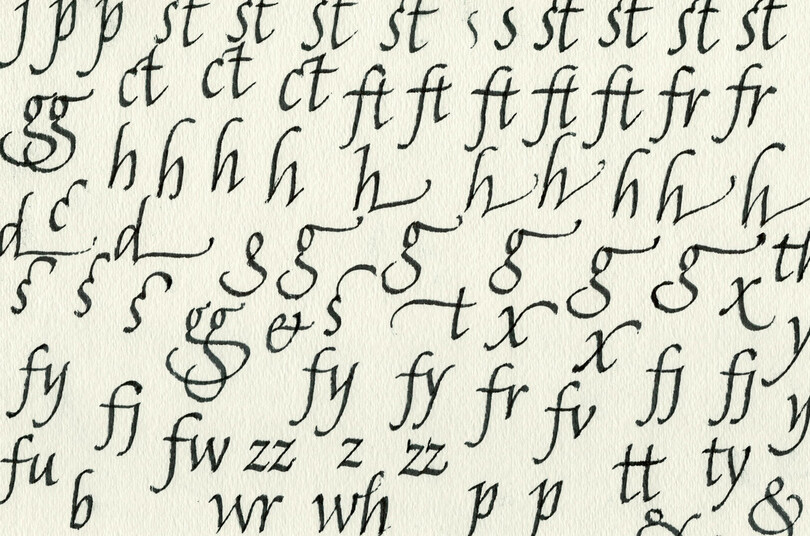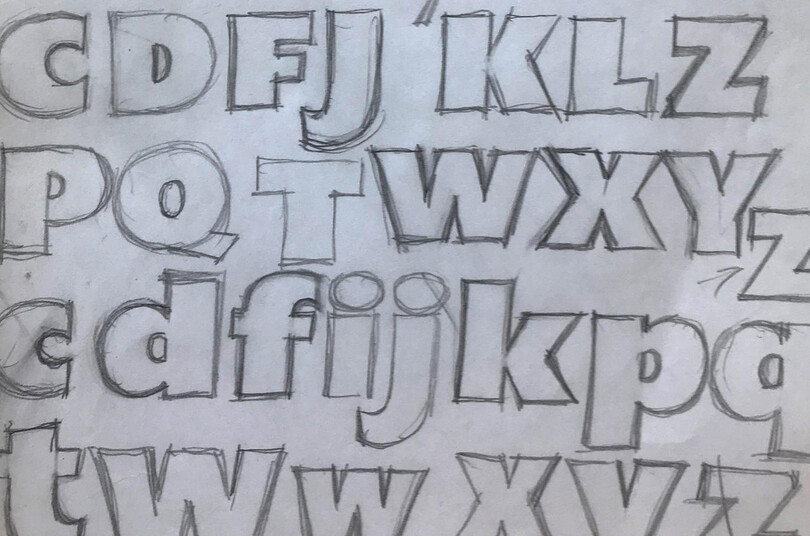
Hinter den Zeichen: Carl Crossgrove, Monotype Studio.
„ Bei der Entwicklung von Exklusivschriften für Unternehmen beginnen wir meist mit dem Markenkern und dem Bild, das die Konsumenten von der Marke haben. Außerdem klären wir, in welchen Umgebungen und Märkten die neue Schrift in Zukunft eingesetzt werden soll. “
Carl Crossgrove
„Hinter den Zeichen“ ist eine Serie von Designer-Interviews, in der die Schöpferinnen und Schöpfer der Fonts vorgestellt werden, die wir lieben und gerne benutzen.
In dieser Folge stellen wir Carl Crossgrove vor, Senior Type Designer beim Monotype-Studio. Von Carls frühem Interesse an Kalligrafie und Zeichnen, bis zu seiner Schul- und Hochschulzeit, als er bildende Kunst und Buchgestaltung studierte, faszinierten ihn dauerhaft die Form von Buchstaben. Neben der Erstellung neuer Schriften für die Monotype Library entwirft Carl auch Exklusivschriften, wobei er an zahlreichen Corporate-Branding-Initiativen mitgewirkt hat.
Erfolgreich starten
Die meisten neuen Schriften entstehen, weil es eine Lücke in der breiten Palette des Font-Angebots zu füllen gilt. Die Ursachen hierfür sind vielfältig: Manche Schriften werden eigens für bestimmte Aufgaben, neue Medien oder Umgebungen entwickelt; andere, um ein bestimmtes Gefühl oder eine Stimmung auszudrücken. Sehr häufig werden auch vergessene Entwürfe wiederentdeckt und für die Herausforderungen des digitalen Zeitalters aktualisiert und erweitert.
Am Beginn eines jeden Projekts steht der ständige Austausch mit Designern und Schriftnutzern, um genau zu verstehen, was sie benötigen und wie sich dies auf die Entwicklung der Schrift niederschlägt. Im Monotype Studio gibt es über 50 Menschen, die täglich Buchstabenformen „ein und ausatmen“. Carl ist einer von ihnen.
Wie viele Schriftentwerfer beginnt er mit einer handgezeichneten Skizze, bevor der Prozess am Bildschirm fortgeführt wird. „Ich habe schon immer gerne gezeichnet, auch Buchstaben, also ist das Skizzieren und Korrigieren der Beginn jeder neuen Schrift. Manchmal zieht sich dieser Prozess, mit nur wenigen Buchstaben, über eine lange Zeitspanne hin. Manchmal ist die Grundidee schnell entwickelt, und ich lege in einer Sitzung die Basis für Groß- und Kleinschreibung, deren Kursivformen  sowie das Strichstärken-Modell.
Schriftskizze
„Manche Entwürfe sollen eine ganz spezielle Stimmung transportieren“, erläutert Crossgrove. „So habe ich beispielsweise Amarone entworfen, um eine Lücke im dichten Feld der Schreibschriften zu füllen – kalligraphisch und ausgefranst, aber doch gut lesbar. Die Blockschrift Cavolini wurde speziell für kleinere Bildschirme weiterentwickelt; ursprünglich war sie als Betriebssystem-Font für die Handschrift-Erkennung eines PDA-Notepads gedacht: So bietet sich stets ein Spektrum an Aufgaben und Varietäten für Schriften an.“
Er ergänzt: „In der Papier-und-Stift-Phase, wo es vor allem um die Konturen der Buchstaben geht, erreicht man nur einen gewissen Grad an Vollständigkeit: alles noch ziemlich provisorisch und chaotisch. Solange die Umrisse nicht gefüllt sind, bleibt weitgehend unklar, wie die Schrift irgendwann mal schwarz auf weiß wirken wird.“
Zusammen mit Charles Nix und Juan Villanueva war Crossgrove Teil des Monotype Studio-Teams, das Walbaum restaurierte, eine viel zu wenig beachtete, 200 Jahre alte und dennoch zeitgemäße Serif-Familie.  Obwohl solche Revivals auf vorhandenem Vorlagen basieren und nicht auf einem weißen Blatt entstehen, haben sie das gleiche Ziel wie komplett neue Designs: eine Lücke zu füllen beziehungsweise etwas Neues ins Spiel zu bringen..
Im Falle von Walbaum ging es darum, ein prächtiges Arbeitstier für das digitale Zeitalter zu modernisieren, so dass man ihre Wärme, ihren Charakter und ihre vielfältigen Verzierungen und Schnörkel neu genießen kann.
„Wir fanden es bedauerlich, dass die Schönheit und Nützlichkeit der Originale durch jahrzehntelange Formatkonvertierungen im Wesentlichen verloren gegangen sind und sich von den Originalen entfernt hatten“, ergänzt Crossgrove. „Unser Type Director Charles Nix  reiste rund um die Welt, um Originalmaterial zu beschaffen. Wir beide untersuchten und vermaßen gewissenhaft die Originale, um sicherzustellen, dass die digitale Neuinterpretation den Geist der Ursprungsentwürfe atmet.“
Für Marken entwickeln
Schriftgestalter werden häufig auch von großen Unternehmen gebeten, eine Lücken zu schließen. Exklusivschriftn sind ein wesentlicher Bestandteil des Portfolios vom Monotype Studio, darunter aktuelle Projekte für Santander, Alibaba, Tencent und Toyota.
Die meisten Marken erwarten, sich mit einer eigenen Schriften vom Wettbewerb abzuheben und ihren Bekanntheit zu festigen. Oder sie wollen die Lesbarkeit quer durch eine Vielzahl von Geräten und Umgebungen (oder beides) verbessern. Manche Marken expandieren gerade in neue Regionen, andere führen eine Umbenennung durch oder ergänzen ihre Palette um neue Produkte. In jedem Fall entwickelt das Monotype-Studio eine enge Partnerschaft mit den Auftraggebern, um die individuellen Herausforderungen zu verstehen und die Markenstimme weiterzuentwickeln.
„In meiner Zeit als Schriftdesigner habe ich viele Leute kennengelernt, die ihre eigenen Studios gegründet haben. Natürlich genießen sie dadurch ein paar Vorteile des Unternehmertums, aber ich bin mit meinem Arbeitsplatz zufrieden“, sagt Crossgrove. „Im Laufe der Jahre habe ich an Projekten gearbeitet, die ich als Selbstständiger nie bekommen hätte. Zum Beispiel an den Google-Projekten Noto Sans und Noto Serif, an den E-Text-Adaptionen einiger Bibliotheksklassiker, natürlich auch an Walbaum und vielen kundenspezifischen Projekten.“